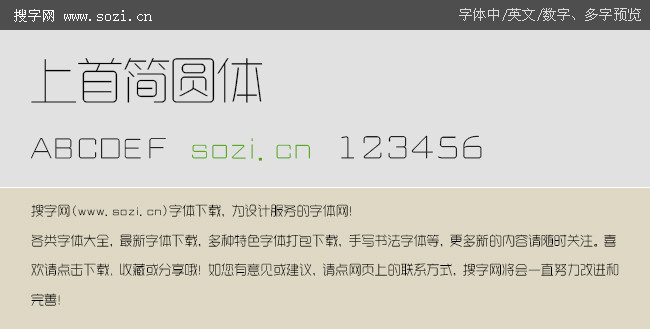
上首簡(jiǎn)圓體
搜字網(wǎng)給大家提供一款上首簡(jiǎn)圓體中文字體下載,上首簡(jiǎn)圓體字體整體特征呈方圓形,筆畫(huà)粗細(xì)勻稱,字體下方轉(zhuǎn)角處作圓角處理,字體辨識(shí)度高,筆畫(huà)圓潤(rùn)流暢,看上去軟萌可愛(ài),帶著幾分童趣,沒(méi)有攻擊性,給人舒適隨和的感覺(jué)?蓱(yīng)用于各類報(bào)紙、雜志、廣告等正文設(shè)計(jì)。